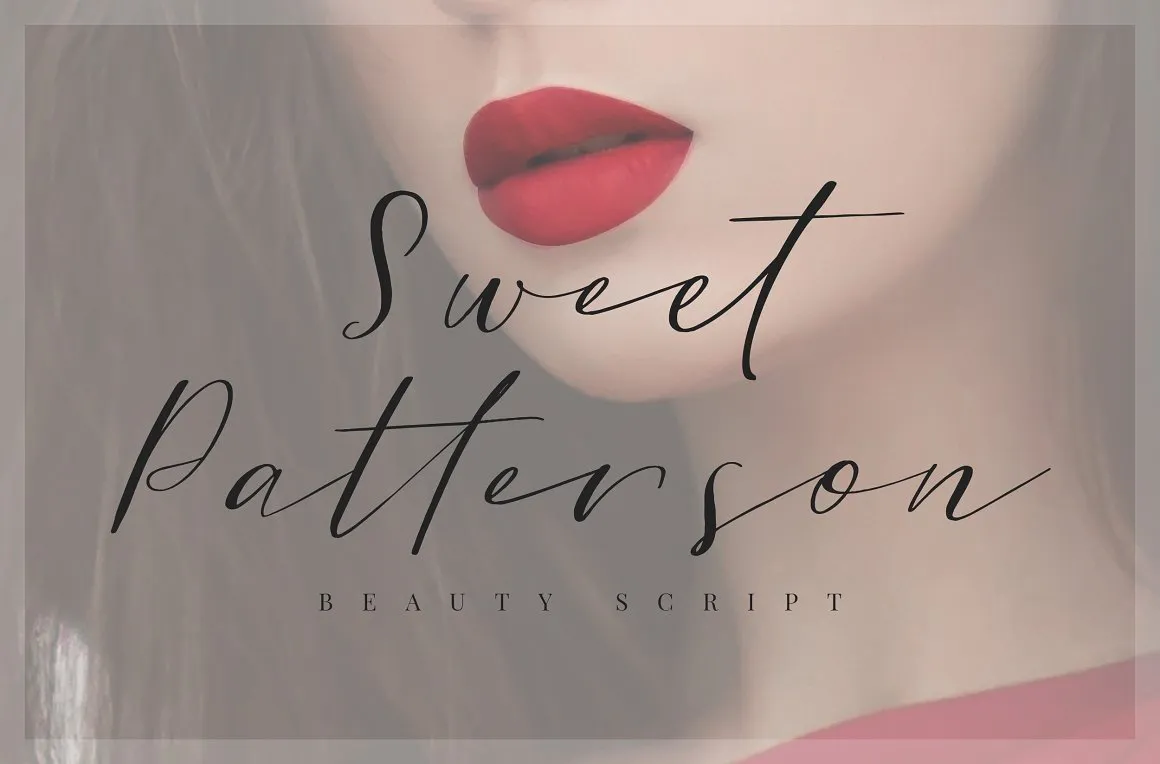
A Sweet Patterson Script Font é uma elegante tipografia script moderna que vai adicionar um toque romântico a qualquer projeto. Esta fonte foi criada pelo talentoso designer 178-MC, inspirado no trabalho de Ian Irwanwismoyo. Cheia de romantismo e beleza, Sweet Patterson é perfeitamente adequada para aplicar em tudo que exige um toque de amor e personalidade: desde logotipos e rótulos de embalagem até cartões de aniversário e design de moda. É uma fonte perfeita para aqueles momentos especiais onde você deseja expressar carinho ou transmitir mensagem de forma única, tornando suas criações ainda mais memoráveis e sofisticadas. Não importa se estiver criando um site profissional, um cartão de visita ou simplesmente decorando seus documentos pessoais, Sweet Patterson está aqui para lhe dar o toque final perfeito.